「絵本」の雰囲気にぴったりな日本語フリーフォント
今回は、やさしく温かみのある世界観を演出できる「絵本」の雰囲気にぴったりな日本語フリーフォントをご紹介します。
絵本の表紙やタイトルには、物語の雰囲気を伝える大切な役割があります。手書きのような素朴な文字や、丸みのあるかわいらしいフォント、少し不揃いで味わいのあるデザインなど、文字の印象ひとつで物語の世界へ引き込む力が生まれます。子ども向けはもちろん、大人向けの絵本やナチュラルなデザインとも相性抜群です。
今回は、やさしさやぬくもり、わくわくする冒険心など、絵本らしい世界観を表現できる日本語フリーフォントを厳選しました。絵本の表紙や挿絵、読み聞かせ動画、ハンドメイド作品などにもぴったりなので、ぜひ参考にしてみてください。
子供・幼児向けの「絵本」にぴったりな日本語フリーフォント集
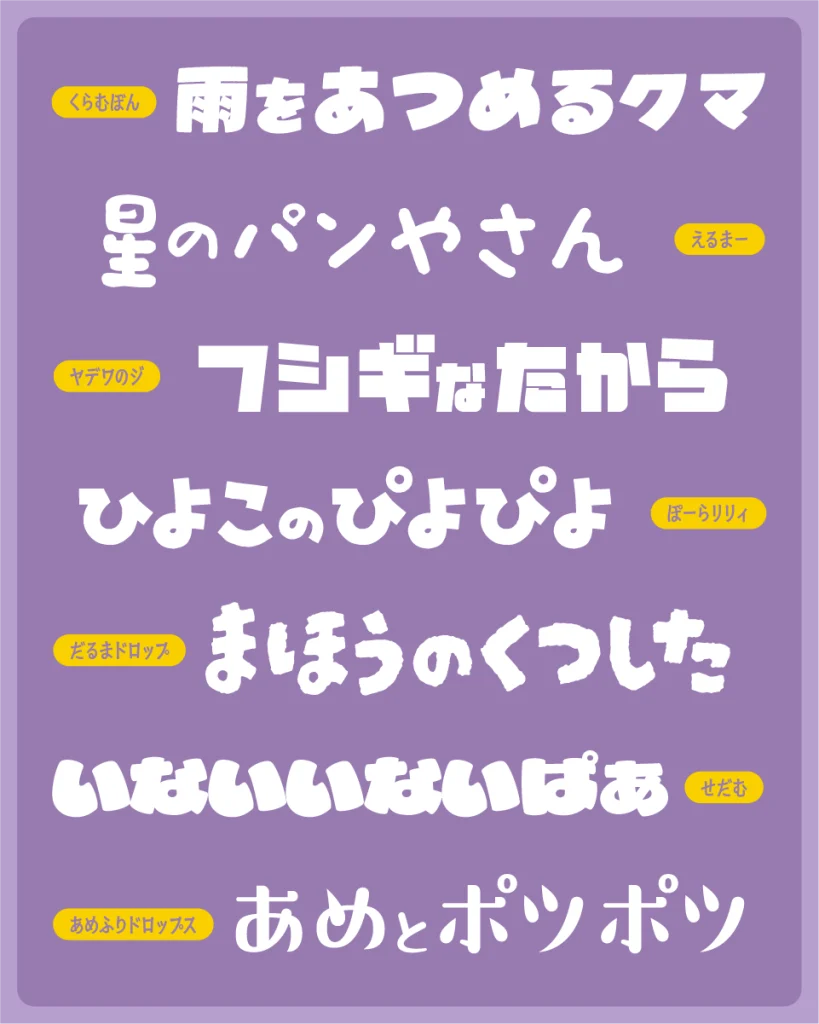
MiFファイト
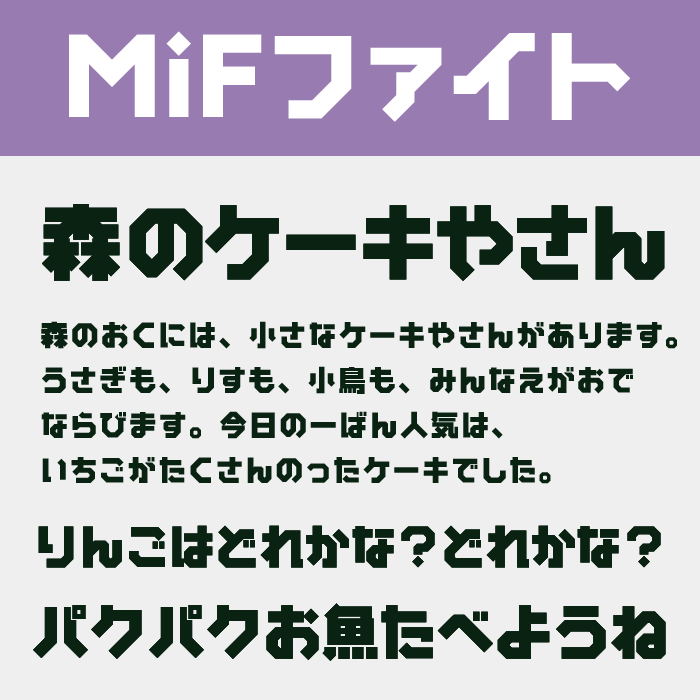
| おすすめの世界観 | ロボット・未来の町・どうぶつの冒険 |
MiFファイトフォントは、角を残しながらも親しみやすく仕上げられたデザインが特徴のフォントです。
ほどよいポップさと高い可読性を兼ね備えており、タイトルから本文まで幅広く活躍します。絵本や子ども向け教材、かわいらしいデザインなど、楽しく読みやすい紙面づくりにぴったりなフォントです。
わんぱくルイカ
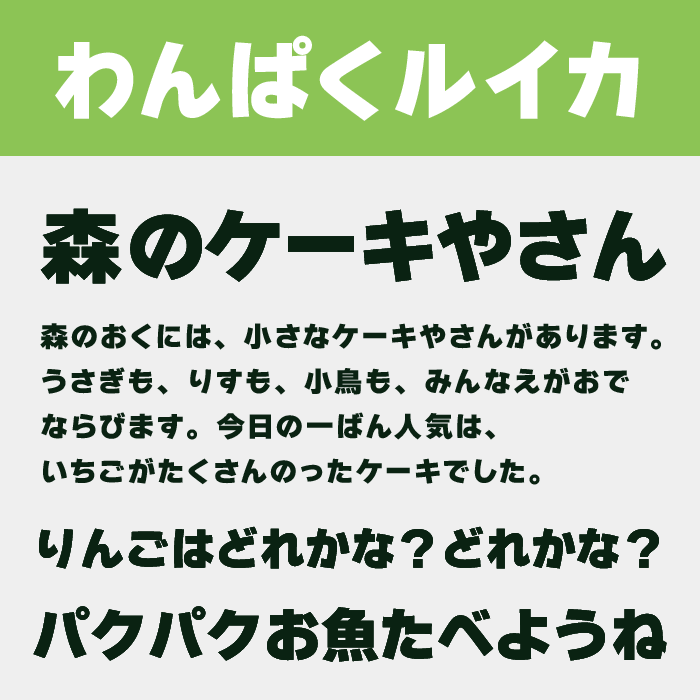
| おすすめの世界観 | 公園・冒険・虫とり・夏休み |
わんぱくルイカは、力強く元気な印象を持つ太めのフォントです。丸みと勢いを兼ね備えたデザインで、子どもたちが元気いっぱい遊ぶ姿を思わせます。絵本やキッズ向けコンテンツ、楽しいイベントの見出しなど、活発で明るい世界観を表現したい場面におすすめのフォントです。
くらむぼん
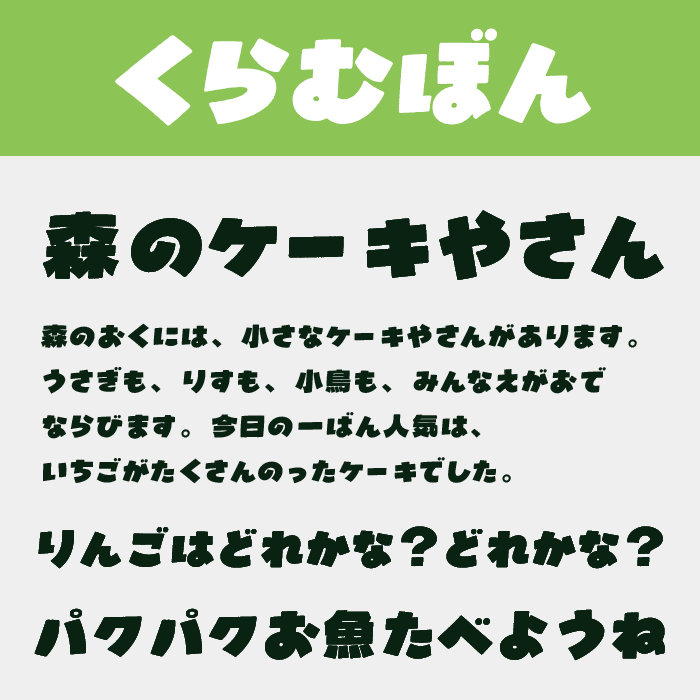
| おすすめの世界観 | お祭り・どうぶつたち・にぎやかな町 |
くらむぼんは、太めで少し傾きのある文字が印象的なフォントです。
元気いっぱいの動きがあり、ページ全体に楽しいリズムを生み出してくれます。絵本のタイトルや子ども向けポスター、イベントなど、にぎやかで楽しい雰囲気を表現したいときにぴったりなフォントです。
えるまー
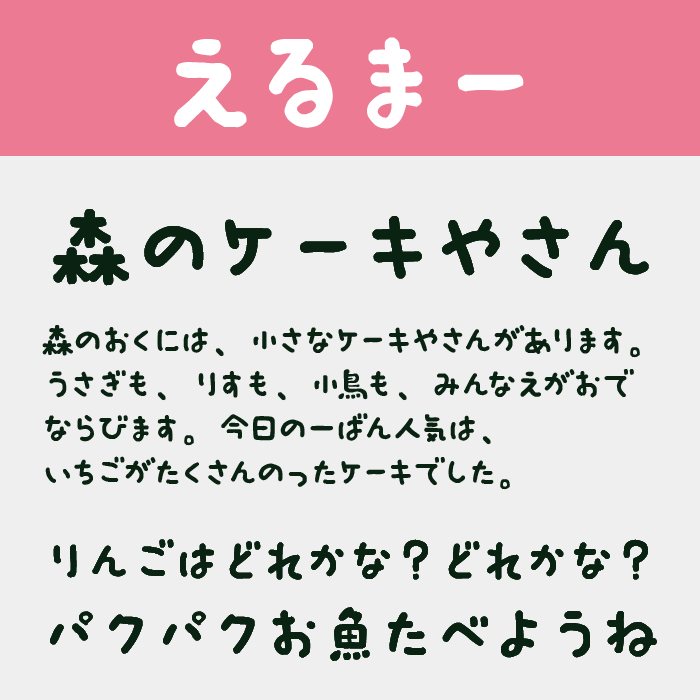
| おすすめの世界観 | 小さな冒険・森・おともだち |
えるまーは、小さな子どもが書いたような自由でのびのびとしたフォントです。文字のゆらぎや丸みが、物語のやさしい空気を自然に引き立ててくれます。絵本やイラスト作品、手づくり感を大切にしたデザインなど、親しみやすさを演出したい場面におすすめのフォントです。
KFひま字
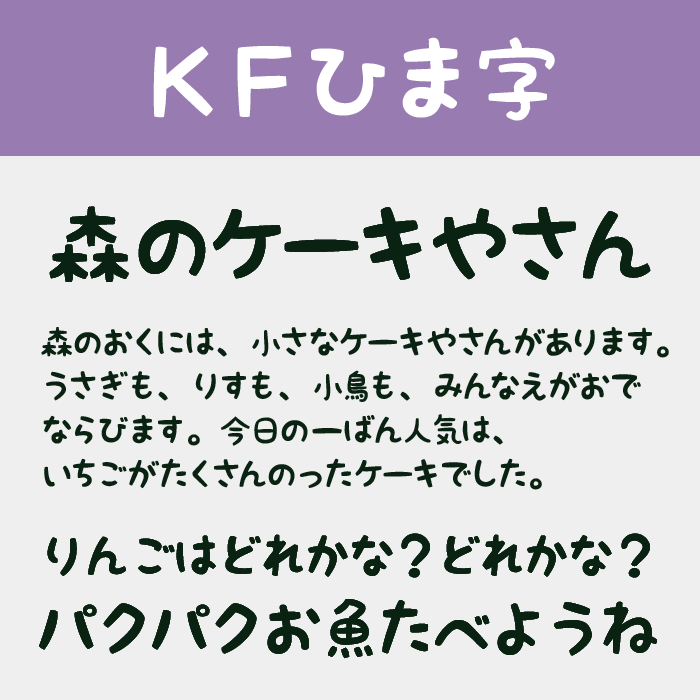
| おすすめの世界観 | 幼稚園・森の学校・動物たち |
KFひま字は、丸みのある線と素朴な手書き感が特徴のフォントです。読みやすさを保ちながらも、子どもが描いたような親しみやすい表情があります。絵本や学習教材、保育園・幼稚園向けの制作など、やさしく温かな印象を届けたい場面にぴったりなフォントです。
はるまき
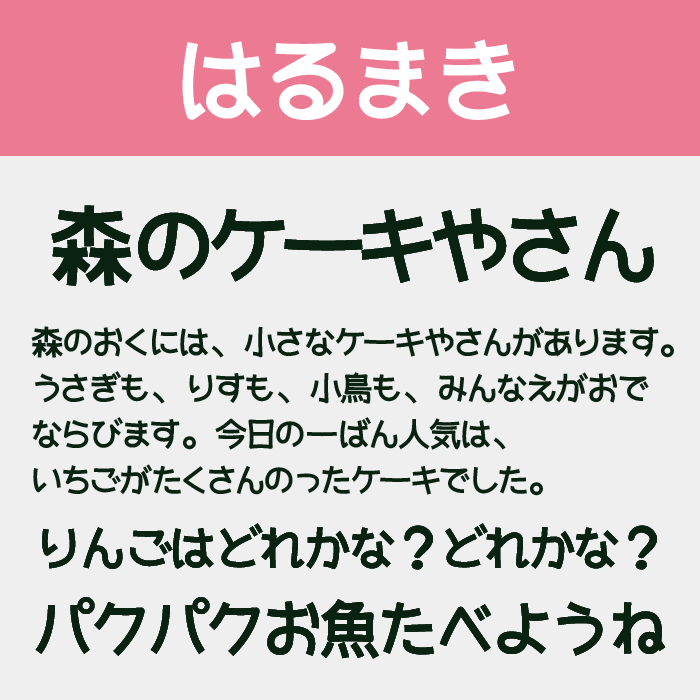
| おすすめの世界観 | 春・花畑・家族の時間 |
はるまきは、自然な手書きの流れを感じられるやさしいフォントです。肩の力が抜けた素朴な表情が魅力で、物語をやさしく語りかけるような雰囲気を演出できます。絵本の本文や見出し、親子向けの冊子など、温もりを大切にしたデザインにおすすめのフォントです。
とりっこ
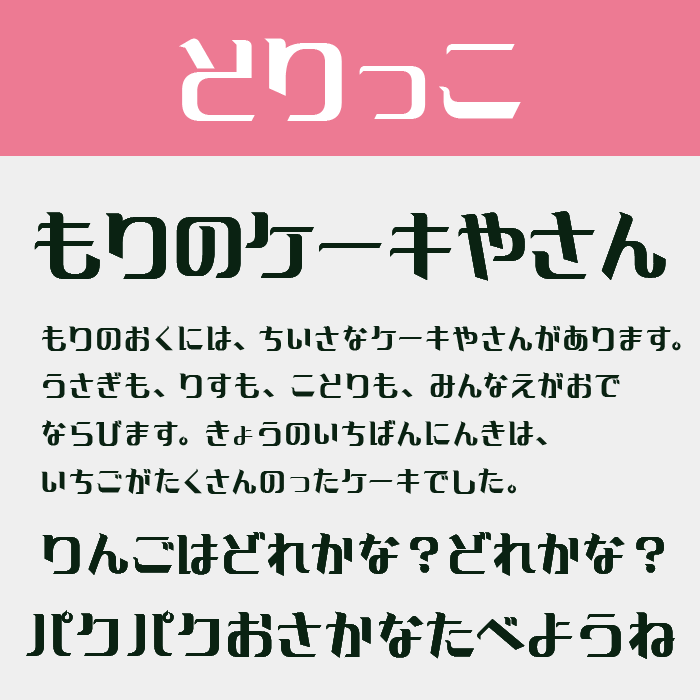
| おすすめの世界観 | 魔法・夜の森・星空 |
とりっこは、クラシカルな雰囲気と独特のデザイン性をあわせ持つフォントです。
文字の一部に鳥のくちばしのようなアクセントが入り、どこか昔ながらの絵本を思わせる味わいがあります。少し不思議で幻想的な物語や、個性を感じさせるデザインにぴったりなフォントです。
あめふりドロップス
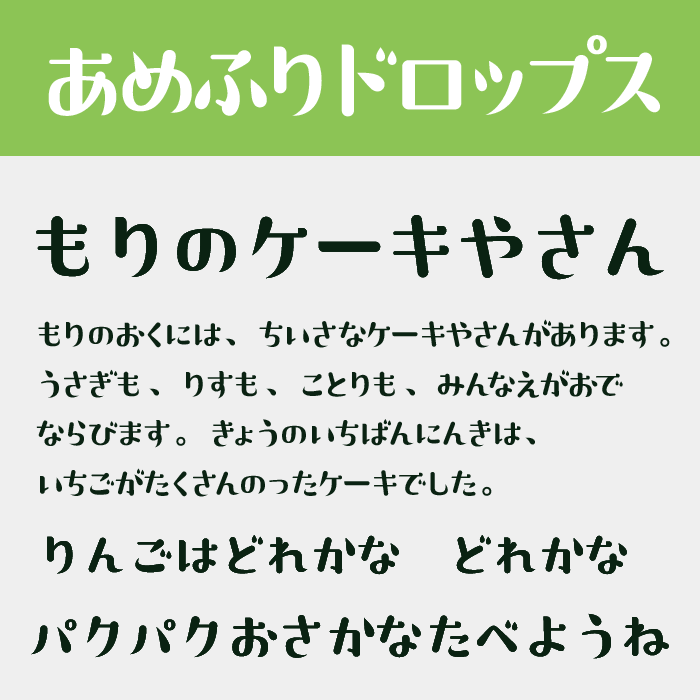
| おすすめの世界観 | 雨の日・四季・自然のおさんぽ |
あめふりドロップス フォントは、水滴がぽたっと落ちる瞬間を切り取ったような、遊び心のあるフォルムがかわいらしい デザインフォントです。
すっきりとした読みやすさを保ちながらも、やさしく穏やかな空気感があります。本文にも使いやすく、絵本の文章や読み物など、自然体で親しみやすい世界観を表現できるフォントです。
もちづき
| おすすめの世界観 | お菓子・森のカフェ・うさぎさん |
もちづきは、おもちのようにふんわり膨らんだシルエットが魅力のフォントです。柔らかく丸い文字が安心感を与え、読み手を優しい気持ちにしてくれます。絵本や子ども向けコンテンツ、お菓子や動物をテーマにしたデザインなど、かわいらしい雰囲気を演出したいときにおすすめのフォントです。
大大大大だぁい好き
| おすすめの世界観 | 友情・学校・毎日の遊び |
大大大大だぁい好きは、名前のとおり元気いっぱいで親しみやすいフォントです。大きく丸い文字がかわいらしく、絵本のセリフやタイトルにもぴったりです。子どもの元気な声が聞こえてきそうな楽しさがあり、明るく笑顔あふれるデザインを作りたいときに活躍するフォントです。
鳩とブリキのワンダランド
| おすすめの世界観 | ふしぎな国・冒険・おもちゃの世界 |
鳩とブリキのワンダランドフォントは、極太な重量感とポップさが共存する、レトロな風合いが可愛らしいデザインフォントです。
文字にリズム感があり、ページを開いた瞬間から物語の世界へ引き込んでくれます。絵本の表紙やタイトル、子ども向けイベントなど、ワクワクする世界観を演出したい場面にぴったりなフォントです。
びーんずフォント
| おすすめの世界観 | お昼寝・家族・小さな幸せ |
びーんずフォントは、やわらかな丸みと手書きらしい自然なバランスをあわせ持つフォントです。文字にほどよいゆるさがあり、読み手に安心感や親近感を与えてくれます。絵本や保育向けの制作はもちろん、優しい雰囲気を大切にしたデザインにも取り入れやすいフォントです。
ヤデワのジ
| おすすめの世界観 | 恐竜・乗り物・元気いっぱいの毎日 |
ヤデワのジは、どっしりとした太さと少し角ばったシルエットが特徴のフォントです。力強さがありながらも親しみやすく、絵本のタイトルや見出しでも存在感を発揮します。文字数が多くても読みやすく、元気いっぱいの子ども向けデザインやポップな作品づくりに活躍するフォントです。
ぽーらリリィ
| おすすめの世界観 | どうぶつの町・遊園地・おもちゃ箱 |
ぽーらリリィは、丸く弾むようなコロコロと丸くて可愛らしい デザインフォントです。
文字ごとに少しずつ動きがあり、ページ全体に楽しさや元気な印象を与えてくれます。絵本のタイトルや子ども向けのイベント、イラストと組み合わせたデザインなど、明るく親しみやすい表現にぴったりなフォントです。
だるまドロップ
| おすすめの世界観 | 森の暮らし・手づくりのお店・田舎の風景 |
だるまドロップは、手作業で描いたような素朴な質感が魅力のフォントです。少し不揃いな輪郭や自然なゆらぎが、絵本ならではの手づくり感を演出してくれます。子ども向けの作品や優しい世界観のデザインと相性が良く、見出しから本文まで、温もりのある雰囲気を表現できるフォントです。
せだむ
| おすすめの世界観 | 森のどうぶつ・お菓子の国・やさしい日常 |
せだむは、ふっくらと丸みを帯びたシルエットが印象的なデザインフォントです。
文字全体にやさしい重みがあり、一文字ひと文字がまるで絵本に登場する動物やお菓子のような愛らしさを感じさせます。タイトルや見出しに使うだけで、読み手が思わず笑顔になるような、あたたかく親しみやすい雰囲気を演出できるフォントです。